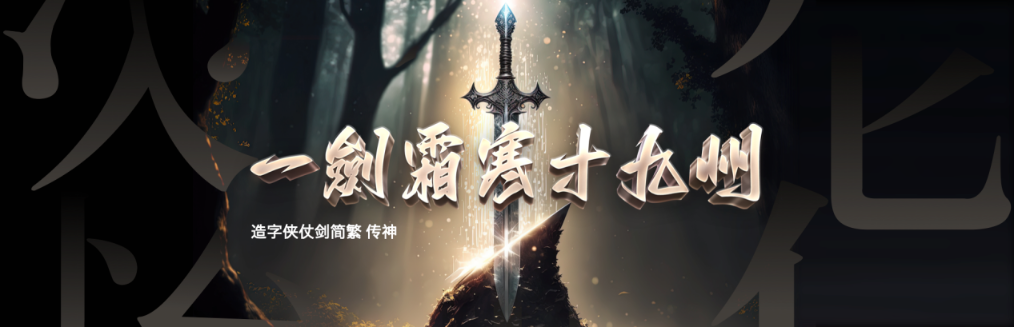
2023年14部仙侠剧爆火,更适合中国设计师的国风海报字体——造字侠伏魔简繁
仙侠是观众最喜爱的题材,经久不衰!2023年14部仙侠剧推荐,《玉骨遥》《长月烬明》《仙剑六》上演流量IP大战。仙侠成为流量关键词,如何挑选合适的字体去做品牌宣传呢?今天,给大家盘点一下近2年的爆款仙侠字体,每一款都是绝绝字。
造字侠伏魔简繁,笔墨浓厚,粗细对比较为明显,字体结构较为中正,字体里笔画的“勾、提、挑、捺”等笔画特点明显、夸张,极具视觉冲击力,单字结构收放自如。如同置身古代三界六道讲妖魔当道之时,以字体为引,开启一路降妖伏魔的奇幻游戏故事。
剑气纵横,潇洒豪气的书法字体——造字侠仗剑简繁。字形稳重、笔画张扬的书法字体。折、提、钩等部首干净利落、高度折叠,颇有豪侠仗剑江湖的潇洒之感。适用于游戏、海报、视频、封面等多种场景。